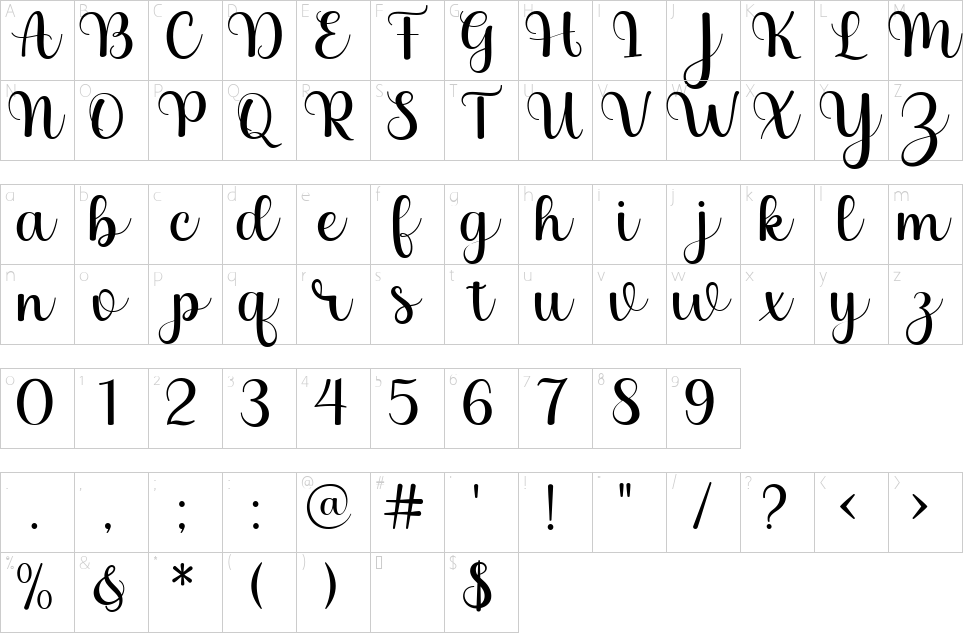
A fonte Megoha é uma escolha agradável para designers gráficos que procuram um estilo elegante e sofisticado para seus projetos. Desenvolvida pelo designer Khaidir, esta fonte gráfica está disponível gratuitamente tanto para sistemas Windows quanto para Mac. Com seu design minimalista e versátil, Megoha é perfeita para criar identidades visuais, texturas e elementos gráficos de alta qualidade. Com sua facilidade de uso e diversidade de estilos, é uma ótima opção para designers de todo o mundo que estão em busca de uma fonte moderna e elegante. Desde que foi disponibilizada, a fonte Megoha já foi baixada 463 vezes, demonstrando a sua popularidade e qualidade entre os designers.